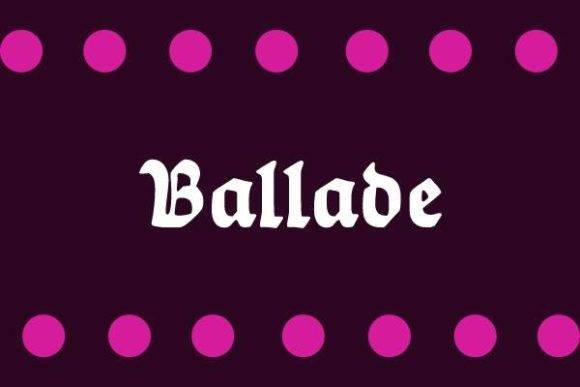
Fuente Ballade para titulares, carteles y proyectos de marca
Fuente de balada
Ballade es una hermosa y distintiva fuente gótica que aporta un toque nítido, elegante y contundente a tus proyectos. Perfecta para realzar tus creaciones, aporta un toque único y elegante a cualquier diseño.
Características:
- Hermoso estilo de letra gótica
- Distinto y nítido
- Elegante y asertivo
Mejora tus diseños con la fuente Ballade y haz que se destaquen con su encanto único.